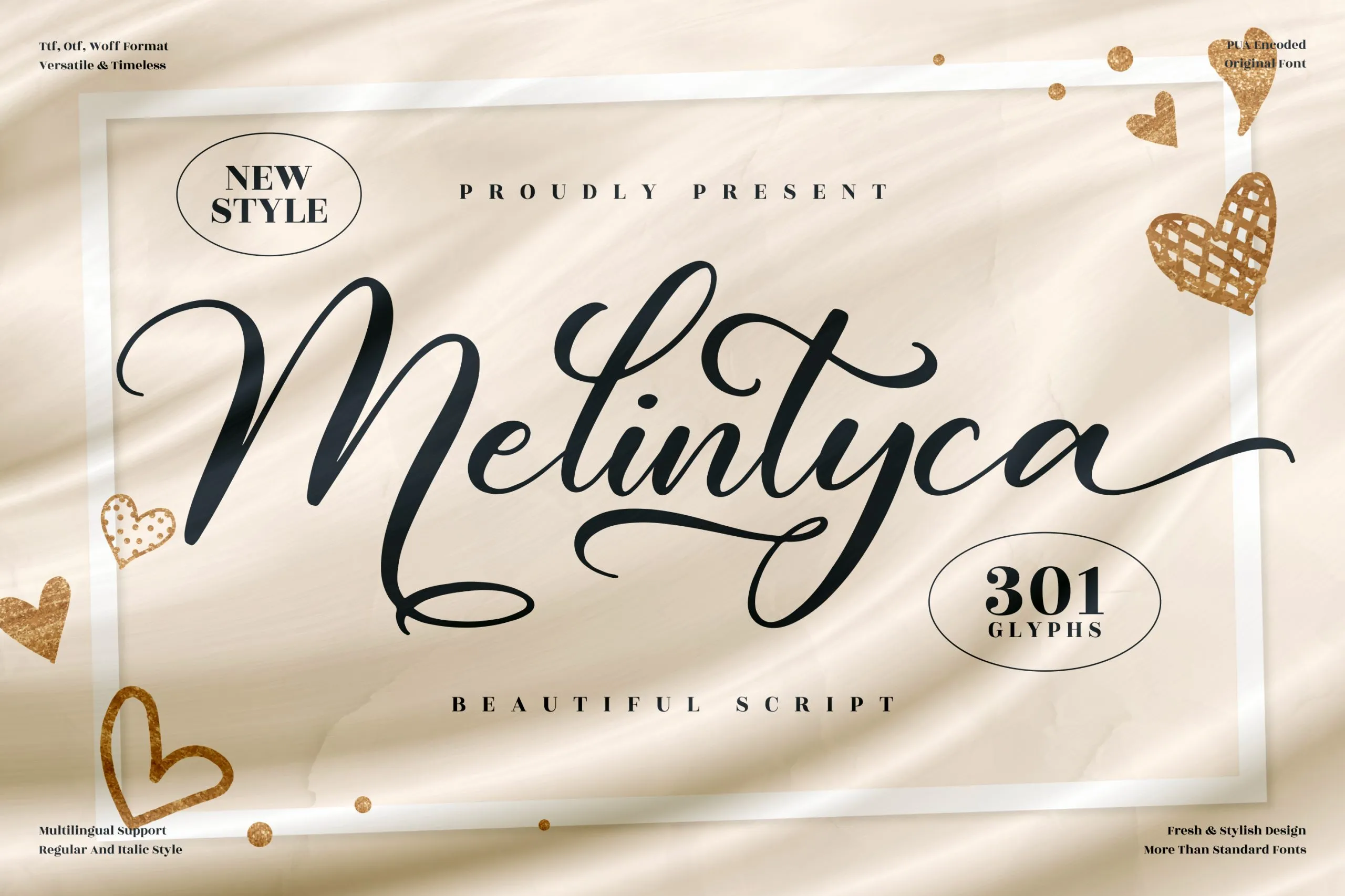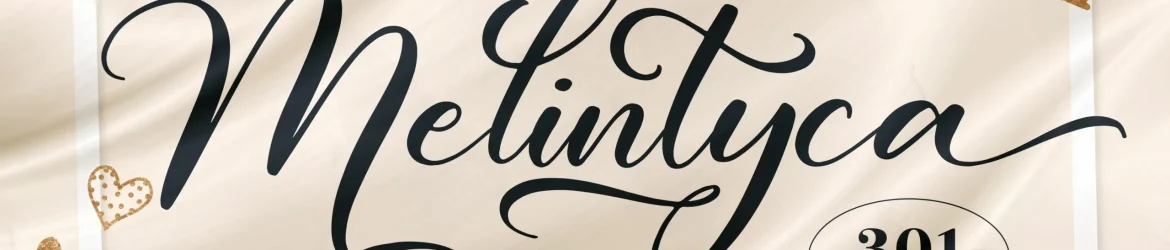
A fonte ‘Melintyca Font’ é perfeita para projetos que exigem um toque romântico e elegante de letra gótica. Esta tipografia especializada não apenas adiciona uma pitada de sofisticação a qualquer projeto, mas também oferece liberdade criativa e diversidade para designers e amantes da arte em todo o Brasil. Suave como uma caligrafia de livro antigo ou vibrante como um desenho digital fresco, Melintyca Font é perfeita para criações que vão desde marcas e identidades digitais até produtos de casa e embalagens. Ela também se destaca em projetos de varejo, artefatos pessoais, cartões de aniversário e muito mais. O designer perspectype criou esta fonte com uma visão cuidadosamente elaborada que valoriza a expressividade do gótico, combinando nuances perfeitas para criar um resultado único. Suas linhas delicadas e sua forma arredondada permitem que as letras sejam usadas em vários contextos sem perder seu encanto característico. Seja você um criador de arte digital ou simplesmente alguém que aprecia uma fonte bonita, ‘Melintyca Font’ tem o potencial de revolucionar a maneira como você expressa seus projetos. Para qualquer projeto que necessite de uma pitada especial de letra gótica romântica, esta font é uma escolha inteligente.